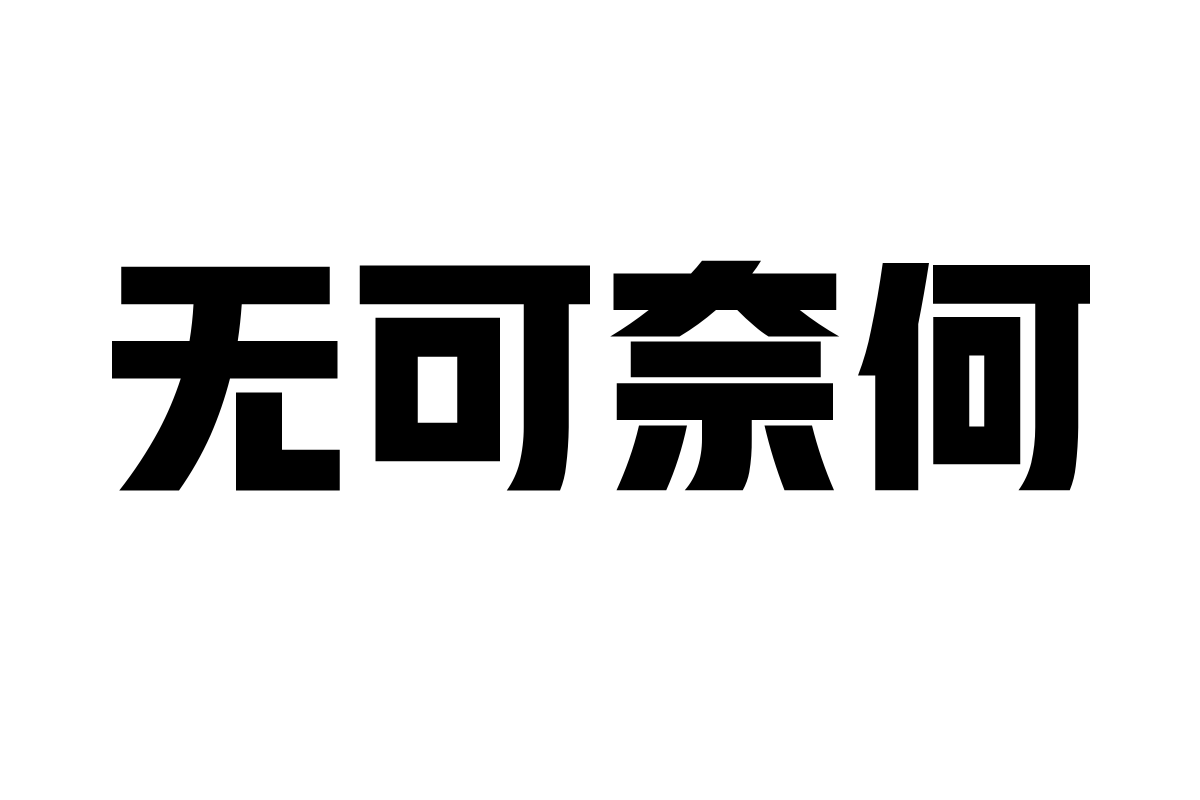
汉仪雅酷黑W是一款具有现代感的中文字体,其设计风格简约而不失优雅。这款字体采用了独特的笔画结构和字形设计,使得整个字体看起来既清晰又易读。同时,它也能够很好地与各种背景和颜色搭配,为设计师提供了更多的创作空间。
该字体的特点在于它的笔画流畅自然,没有过多的装饰元素,使得整个字体显得非常简洁。这使得它在视觉上给人一种轻松、愉悦的感觉,适合用于需要强调简洁、清晰的场合,如网页、海报等。
此外,汉仪雅酷黑W还具有一定的可读性,无论是在小字号还是大字号下都能保持清晰的视觉效果。这使得它非常适合用于需要突出文字内容的场景,如标题、正文等。
总的来说,汉仪雅酷黑W是一款非常适合现代设计风格的中文字体,无论是在网页设计、广告设计还是其他需要强调文字内容的场景中,都是一个非常不错的选择。